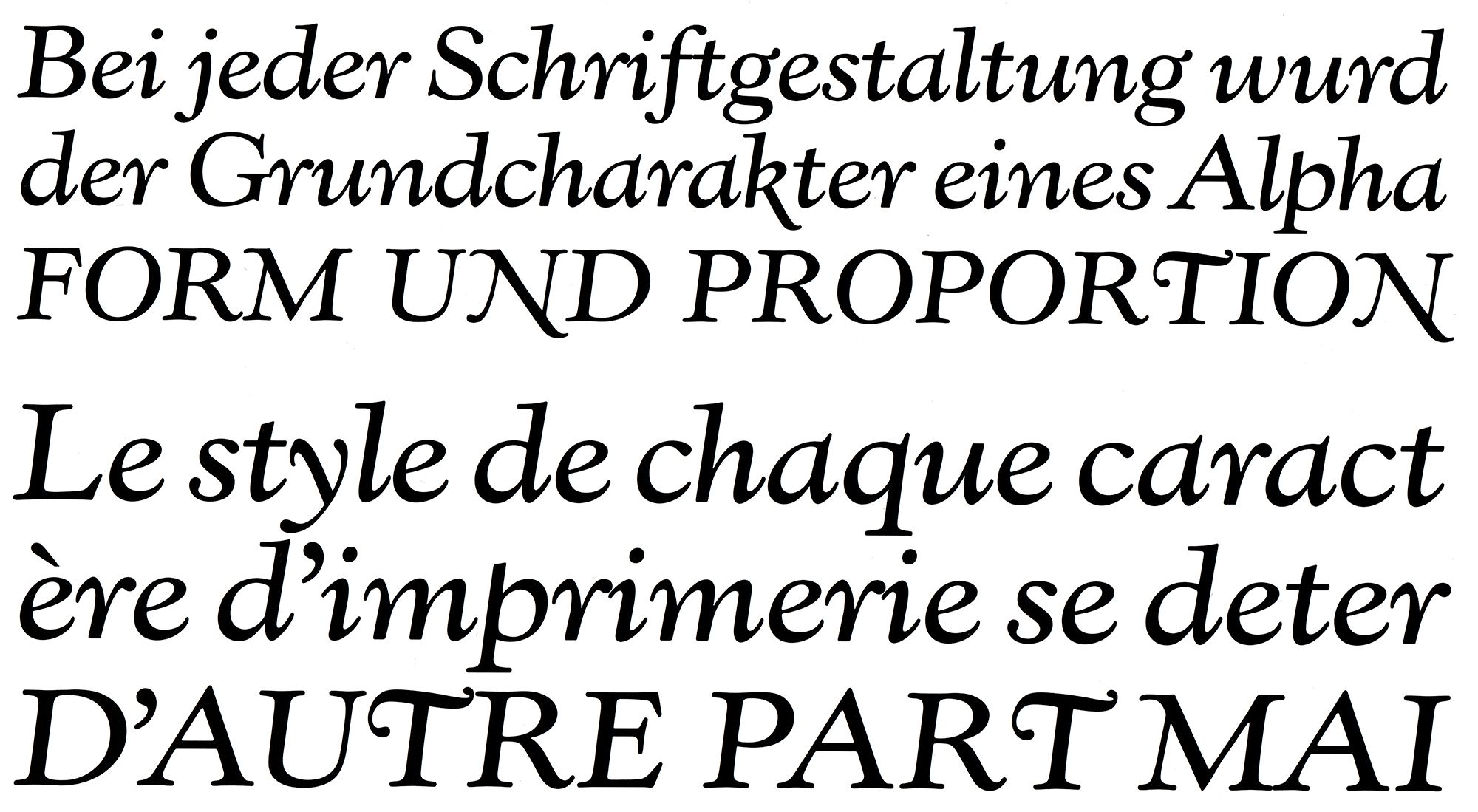
Font-Wiki: Kennerley Old Style
• 1924
• Serifen:
• serif
• Antiqua humanistisch
Die Schrift wurde ursprünglich für Publikationen des Verlegers Mitchell Kennerley geschnitten und in den 1920er-Jahren durch Monotype angeboten und weiter ausgebaut.
Eine digitale Version ist als LTC Kennerley Old Style über P22 erhältlich.